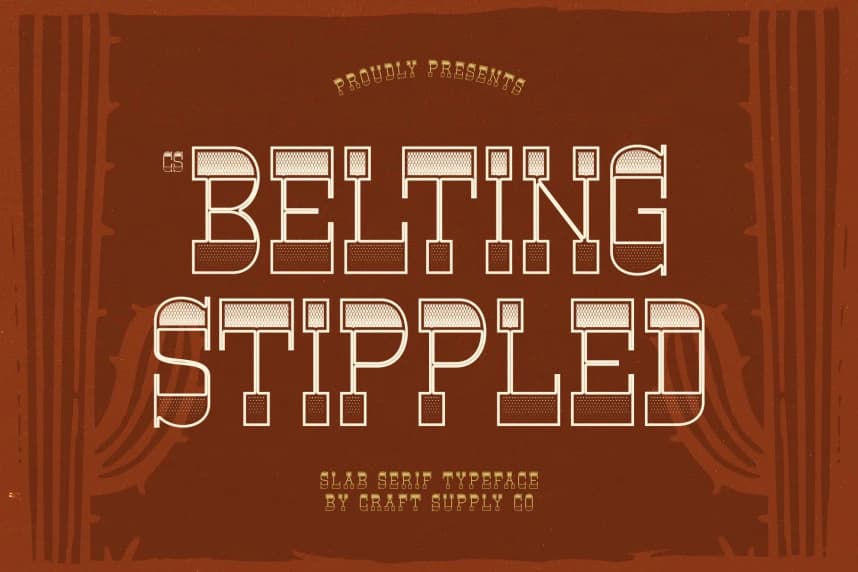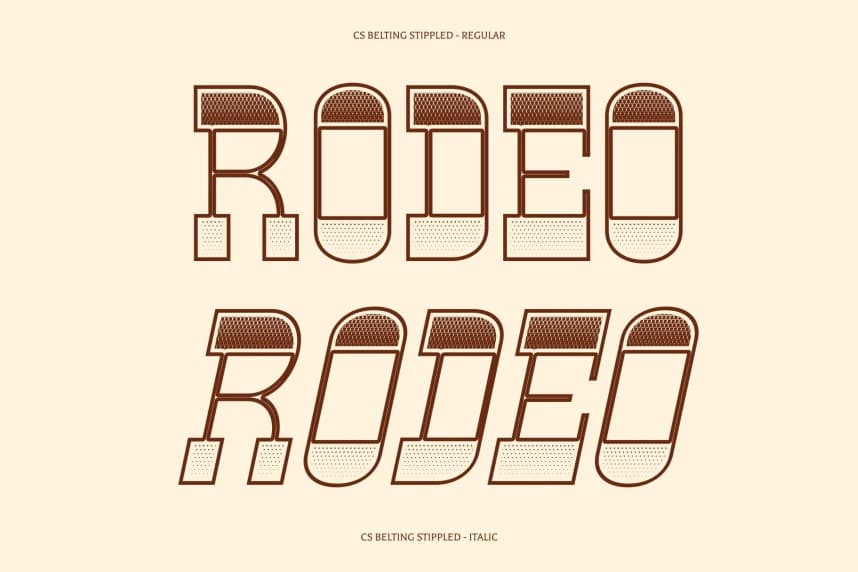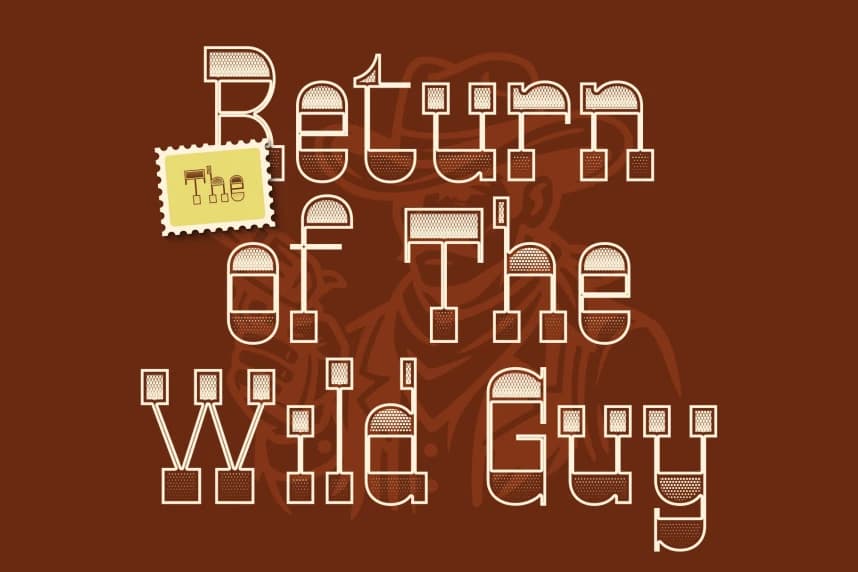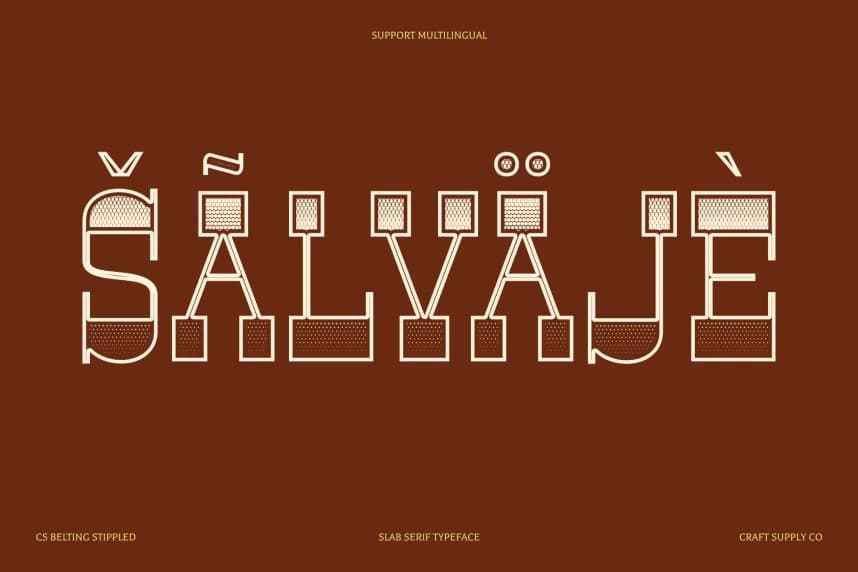
CS Belting Stippled Font
CS Belting Stippled Font – Kalın Gösterim Formunda Sert Batı Ruhu. Western Display Font with Stippled Frontier Character. Bu, Vahşi Batı'nın kontrolsüz ruhunu yansıtan cesur bir Western Display Font'tur.
CS Belting Stippled Font – Sert Batı Ruhu Kalın Gösterim Formunda Western Display Font ile Stippled Frontier Karakteri. Bu, Vahşi Batı'nın yırtıcı ruhunu yansıtan cesur bir Western Display Font'tur.